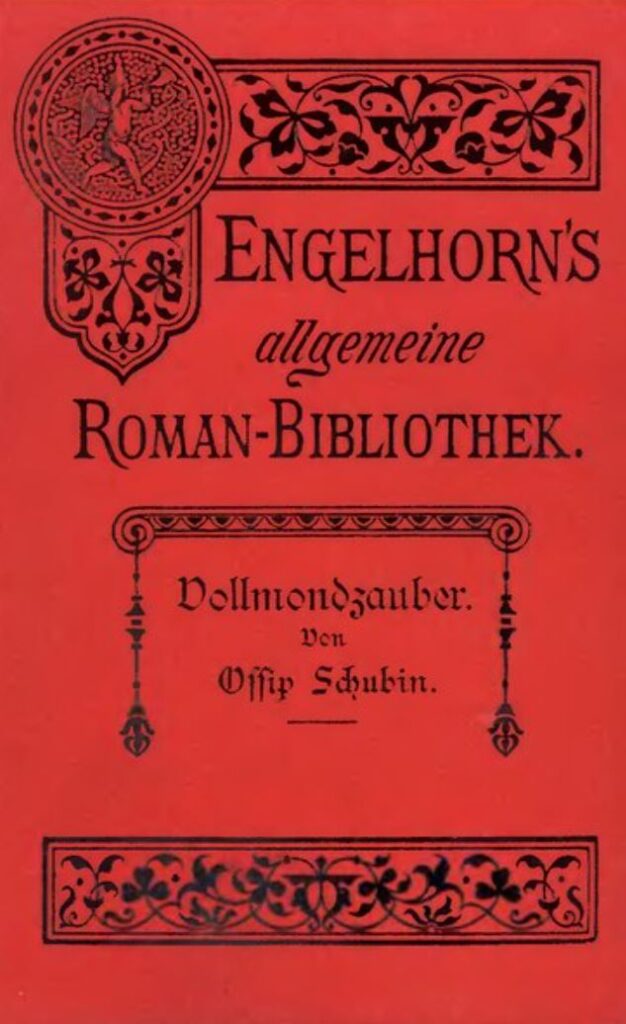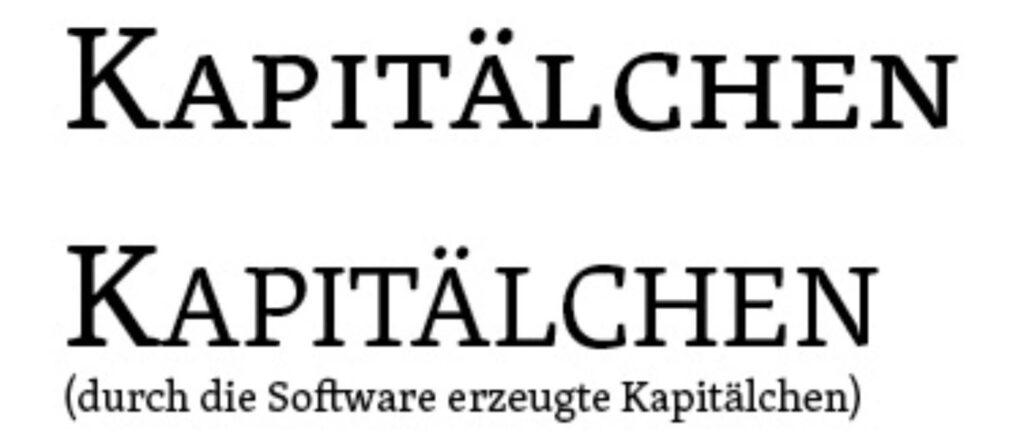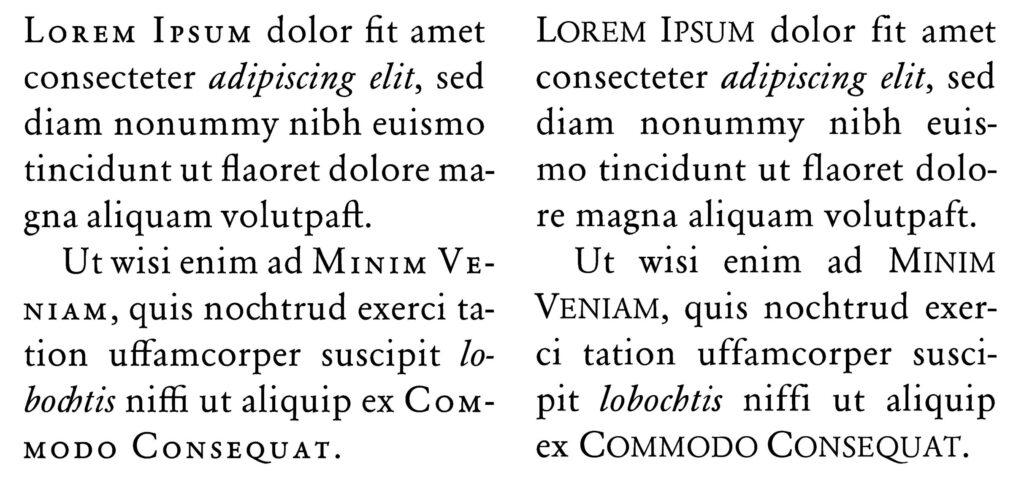
Kapitälchen
Eine der elegantesten Auszeichnungen innerhalb einer Schriftfamilie sind die Kapitälchen. Dabei handelt es sich – wie bei Kursiv- oder Fettschnitten – um einen eigenen Schriftschnitt.
Alle Buchstaben erscheinen in der Form von Versalien, unterscheiden sich jedoch in der Proportion:
• Die eigentlichen Großbuchstaben bleiben unverändert.
• Die „kleinen Versalien“ (ersetzte Gemeine) sind verkleinert und orientieren sich in der Höhe an den Kleinbuchstaben.
• Der Grundstrich ist bei allen Zeichen gleichmäßig und meist kräftiger als bei normalen Versalien.
An dieser Gleichmäßigkeit der Strichstärken erkennt man echte Kapitälchen – im Gegensatz zu elektronisch erzeugten. Viele Layoutprogramme wie QuarkXPress oder Adobe InDesign bieten die Option, normalen Text automatisch in Kapitälchen umzuwandeln. Dabei wird jedoch lediglich der Kleinbuchstabensatz hochgestellt und skaliert. Das Ergebnis sind ungleichmäßig dünne Strichstärken und ein insgesamt disharmonisches Schriftbild.
Falsche Kapitälchen – ein typografisches Vergehen
Zwar tauchen elektronische Kapitälchen bisweilen auch in professionellen Anwendungen oder Werbekampagnen auf, doch erreichen sie nie die Eleganz und Balance echter Kapitälchenschnitte. Ihr Einsatz gilt daher in der Typografie als unsauber – vergleichbar mit künstlich schräggestellten („elektronisch kursivierten“) Schriften. Wer typografisch sorgfältig arbeiten möchte, sollte Kapitälchen ausschließlich in ihrer echten Form verwenden.